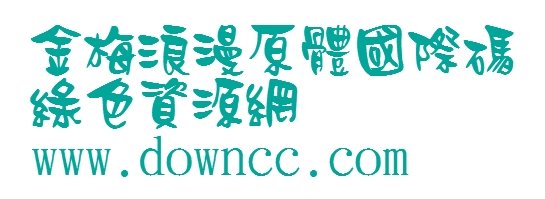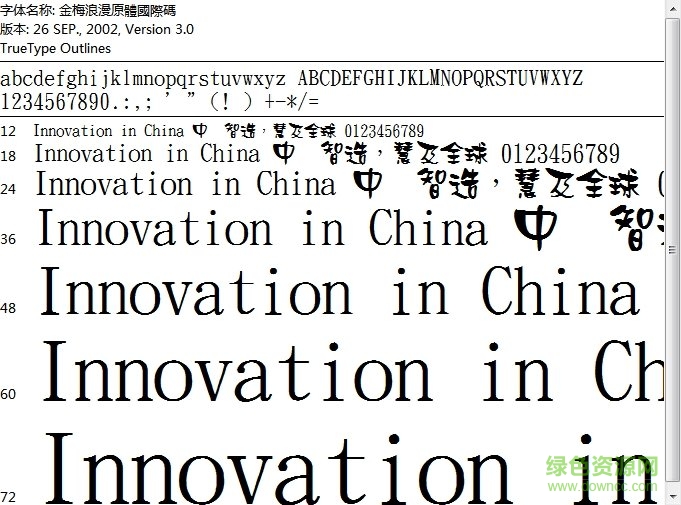
金梅浪漫原體是一款造型大氣、格調(diào)唯美的繁體中文字體,讓漢字變得漂亮起來,筆畫圓潤字跡秀氣,藝術(shù)效果十分不錯,喜歡的朋友就來綠色資源網(wǎng)免費下載吧!
金梅浪漫原體國際碼是一款藝術(shù)設(shè)計字體,字庫中的文字為繁體設(shè)計,金梅浪漫原體國際碼字體可用于廣告設(shè)計字體、網(wǎng)頁設(shè)計字體、包裝設(shè)計字體、 屏幕顯示字體等。